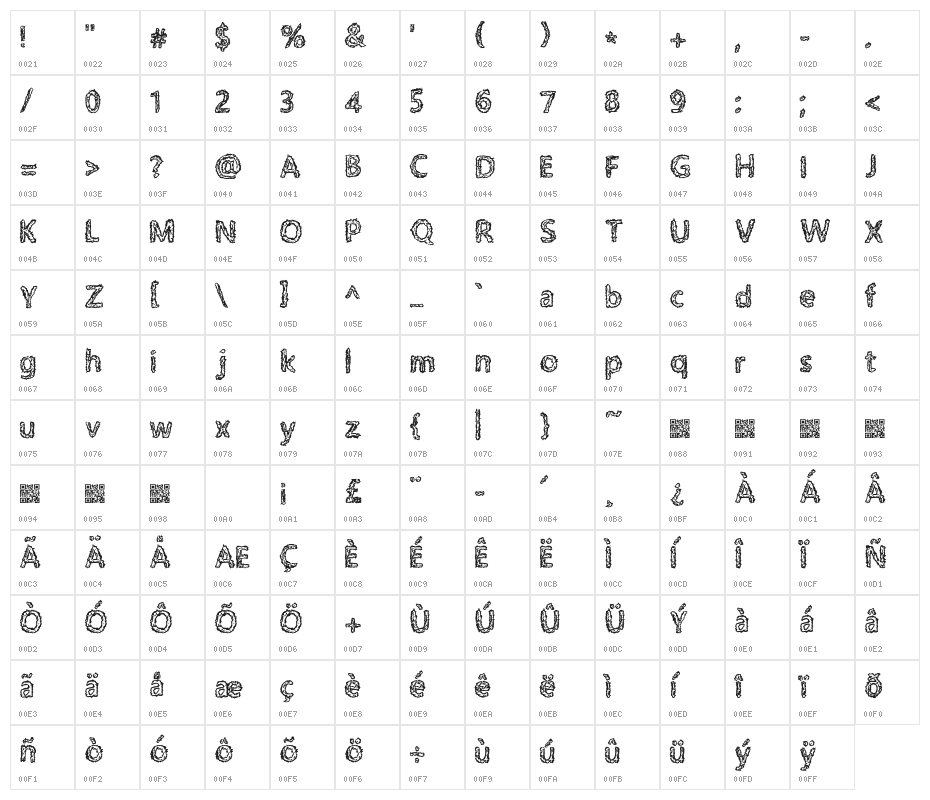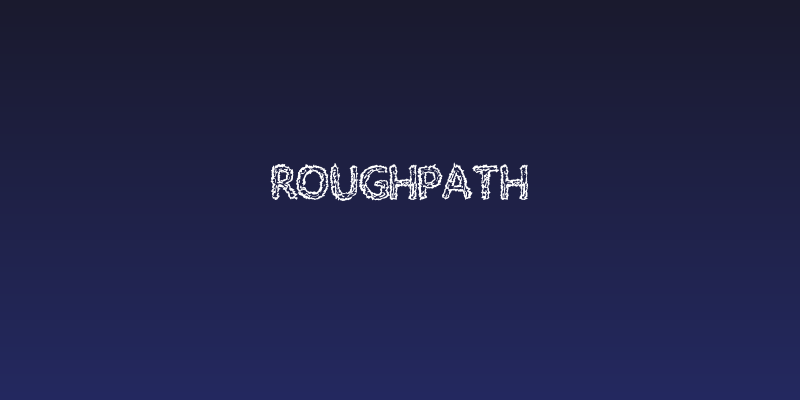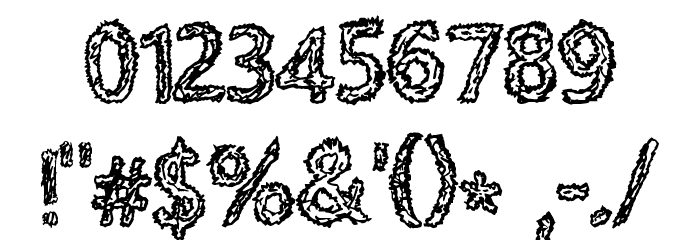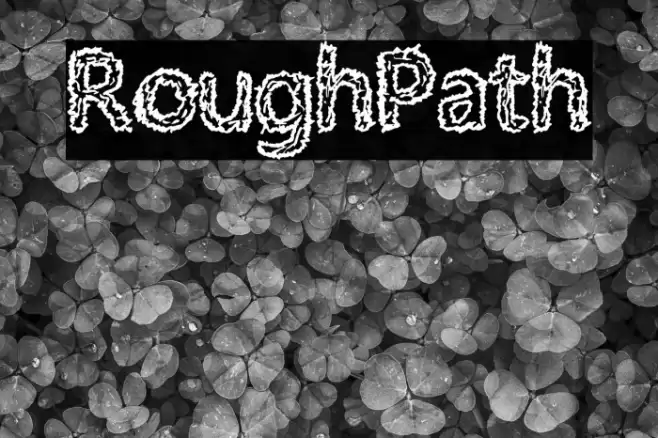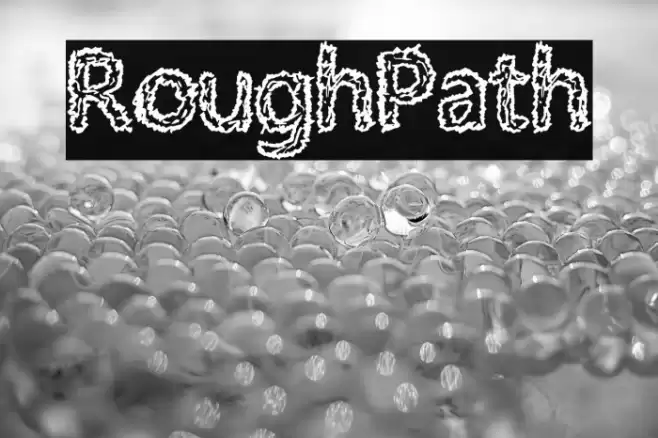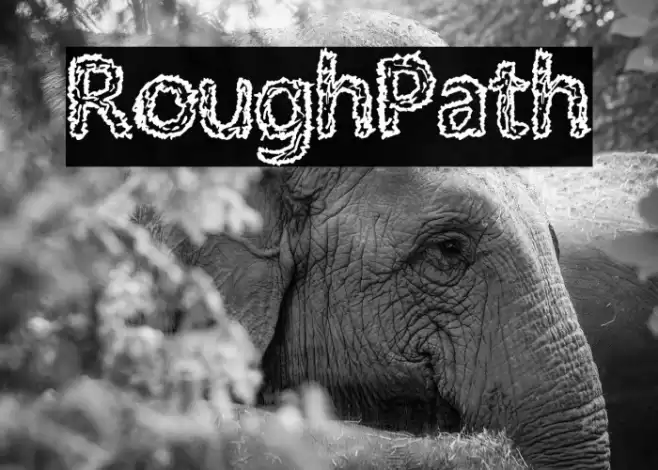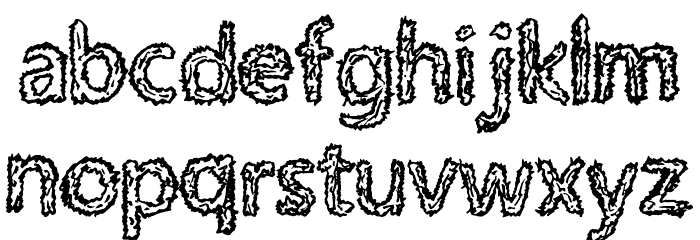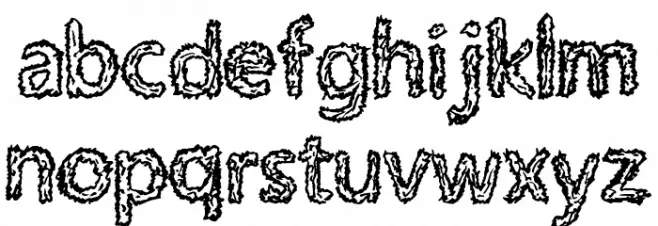
RoughPath Font
✎ Messy
| Caz de utilizare | Headlines, Logos, Artistic projects |
| Proiecte propuse | Ideal for posters, album covers, artistic branding, and creative projects that require a unique and edgy look. |